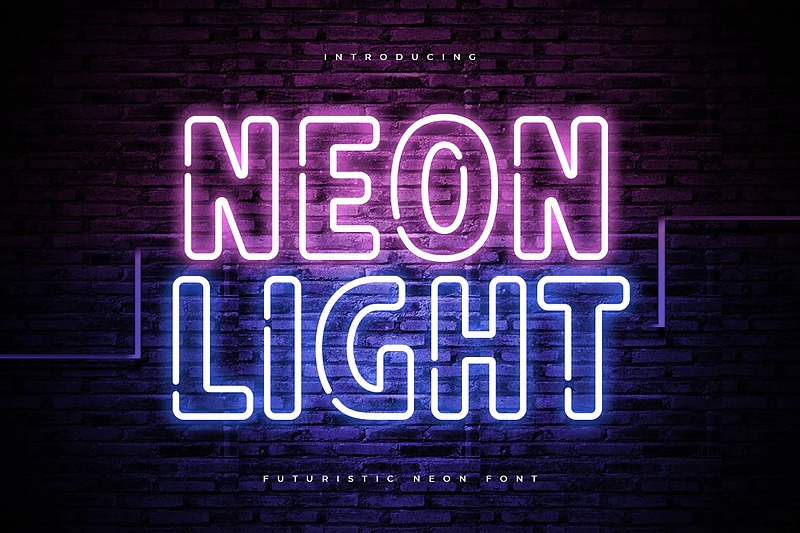
فونت انگلیسی نئون لایت (Neon Light)
معرفی فونت نئون لایت
نئون لایت «چراغ نئونی»، یک فونت نئون آینده‌نگر با فرم‌های مدرن است که طرح‌های شما را منحصربه‌فرد و شیک می‌سازد.
این فونت نمایشی جدید را به طور ویژه برای عناوین، تیترها و نیازهای تایپوگرافی برجسته خلق کرده‌ایم که با کاراکترهای متمایزش، تنوع و سبک‌های مختلفی را به شما ارائه می‌دهد. این فونت برای افزودن سبک و نمای خاص به عناوین شما ایده‌آل است. به طور ویژه برای این فونت، سبک منحصربه‌فرد و حس مدرن را در نظر گرفته‌ایم تا از خلق هر پروژه‌ای که ایده اصلی شما را به نمایش می‌گذارد، لذت ببرید.
ویژگی‌های فونت فیوچرستیک نئون لایت:
• امکانات متعدد برای ایجاد تنوع خلاقانه
• پیش‌نمایش الهام‌بخش برای استفاده از فونت
• شامل حروف تمام بزرگ
• اعداد و علائم نگارشی و چندزبانه
• طبقه‌بندی: سنس سریف
• فاصله‌گذاری: نرمال
• اندازه بهینه: هر اندازه‌ای